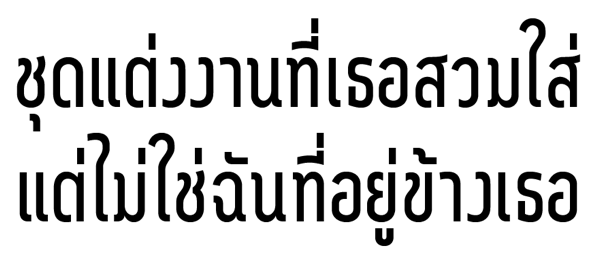
เคยเห็นเป็น ท แบบ flip เลยครับ เมพขิงๆ
๘ แบบหลังคิดถึง nbt เลย
แต่ชอบนะ
๘ แบบหลังนี่เท่ห์ดีมากเลย
ลองทำ ๓ แบบให้จุดหักมันอยู่อีกฝั่งหนึ่งดูมั๊ยครับ
อาจเข้ากันก็ได้นะ เหมือนย้ายข้างมันเลย ลองดูครับ
ขออธิบายภาพรวมก่อนนะครับ ดีเทลค่อยทยอยนำกลับมาให้ดูกัน
อีกหนึ่งรายละเอียดที่เปลี่ยนไปของตัวละตินนะครับ
ผมตัดส่วนโค้งตรงหัวพยัญชนะแบบที่มีในภาษาไทยออก เพื่อให้แยกแยะได้ง่ายขึ้น
แล้วก็เพื่อให้ใช้งานได้อย่างหลากหลายมากขึ้น เป็นทางการมากขึ้น
และ condense ที่กำลังค่อยๆ เป็นรูปเป็นร่าง
พรีวิวคร่าวๆ ครับ
ผมเพิ่มเส้นตรงเข้าไปในแกนทั้งสองข้างของแต่ละตัวอักษร เพื่อช่วยให้ นน. condense ดูแตกต่างออกมาจาก regular อย่างชัดเจน
ไม่ใช่แค่เสมือนจับเอา regular มาบีบเฉยๆ
แน่นอนว่าสัณฐานก็แคบลงด้วย
ได้ความรู้ววว
อ.โม่มาพร้อมสาระเสมอ
แลดูเข้าท่าดี แต่ metric เละเทะมาก
อ่านยากมวาก
ขอรายละเอียดหน่อยครับ
มันเหมือนๆ กันไปหมดน่ะ
พอมองแวบปั๊บ เห็นแต่เส้นตั้งๆ วางอยู่เป็นแผงเลย ต้องตั้งสติแยกแยะว่าตัวอะไรเป็นตัวอะไรในแป๊บนึง
มึนๆ ตาคนแก่
อาจเป็นเพราะช่องไฟในตัวกับช่องไฟระหว่างตัวอักษรมันใกล้เคียงกันเกินไปด้วยแหละ
ว กะ ง ด กะ ต อาจจะไม่เคลียเปล่าครับ
ว กับ ง นี่คิดอยู่เหมือนกันครับ เพราะพอพิมพ์คำว่า วง นี่ สับสนอย่างแรง
ฉ ฉิ่งนี่น่าจะกว้างไปหน่อย
อ กว้างไปนิด